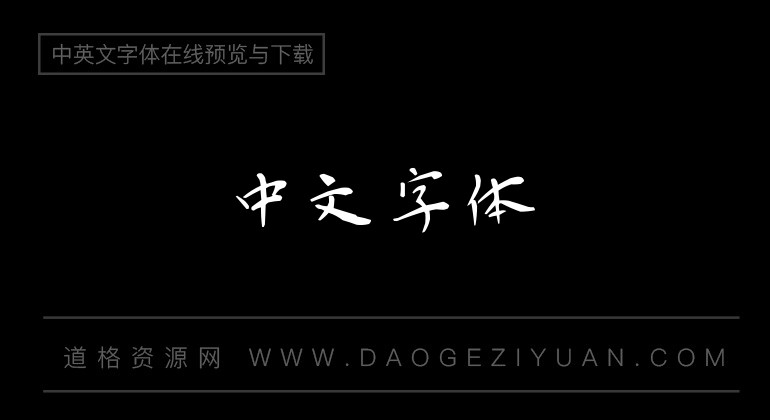
陈学儒浪漫书信简体
陈学儒浪漫书信简体字体是一种汉字字体,由陈学儒设计。这种字体具有浪漫、温暖、精致的特点,适用于书信、海报、小册子等文档的设计。它采用了比较宽松的笔画,每个字体都具有较强的可读性和可辨识性,能够更好地表达文字的内容。此外,它还具有细节处理的特点,能够更好地表达文字的气氛和感情。
陈学儒浪漫书信简体是一款非常不错的手写艺术字体,具有很好的视觉感,适合于文化类的宣传设计、商业类品牌的广告和产品包装设计以及个性化文字排版等较多场景。